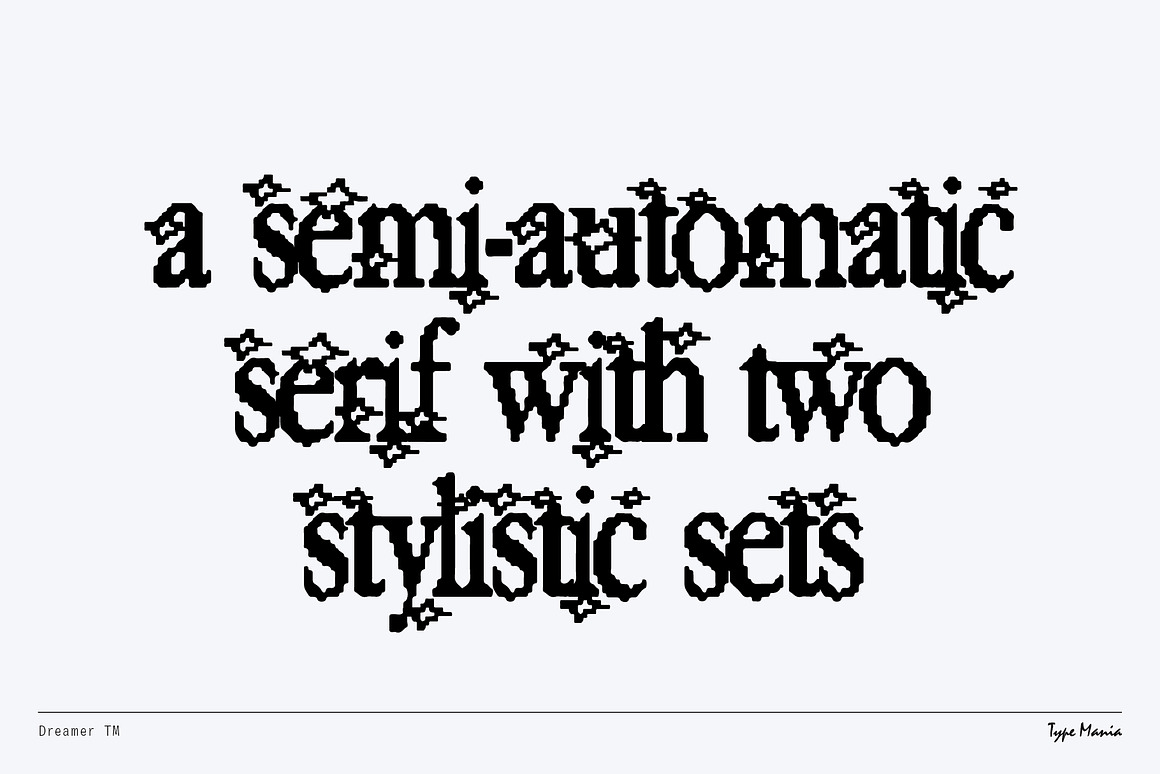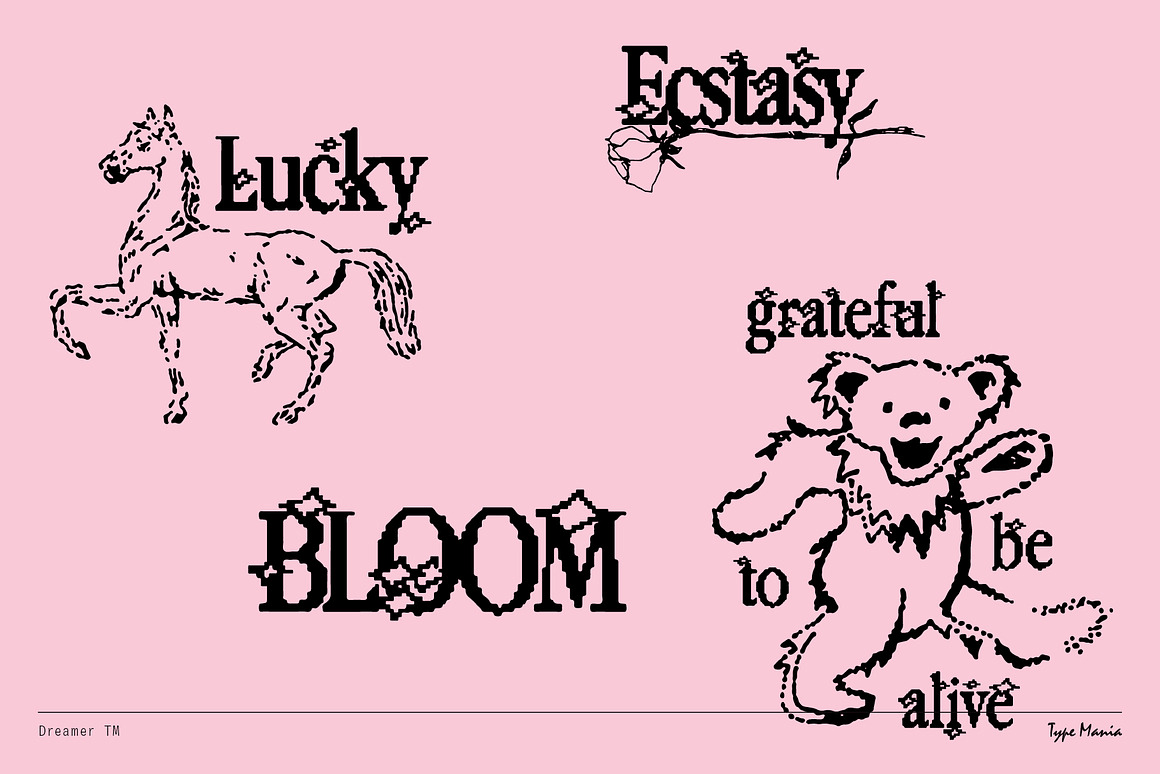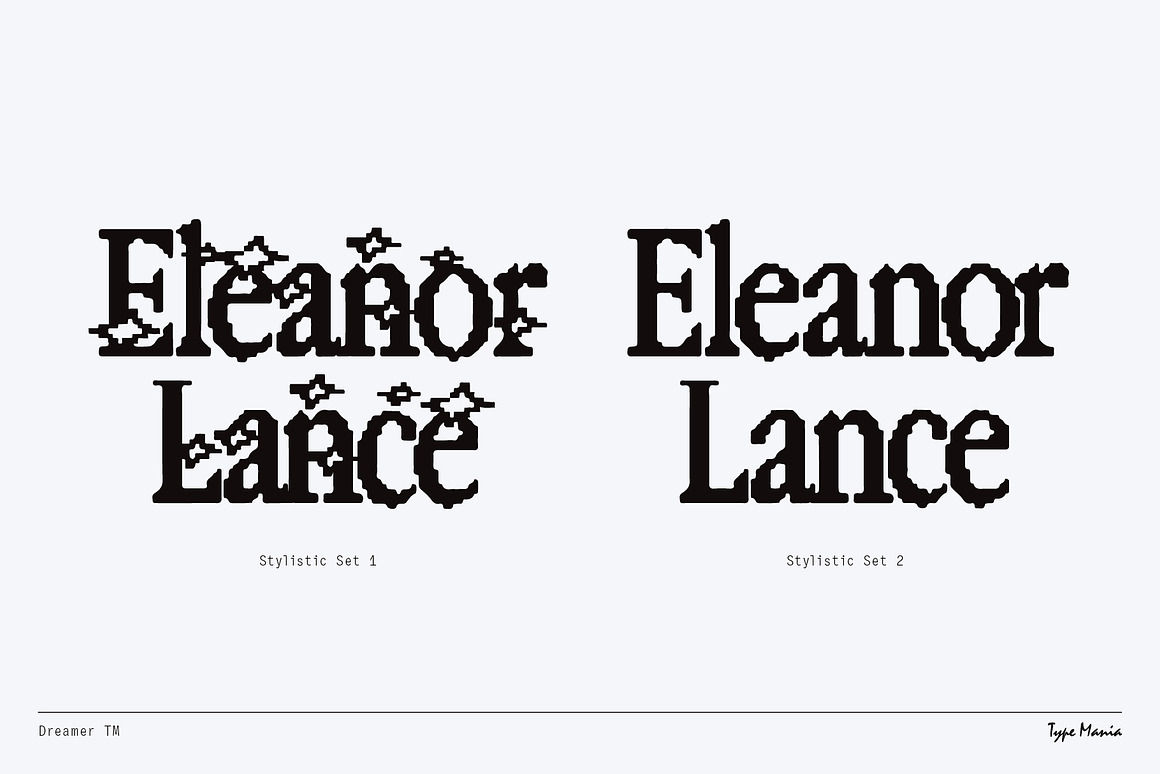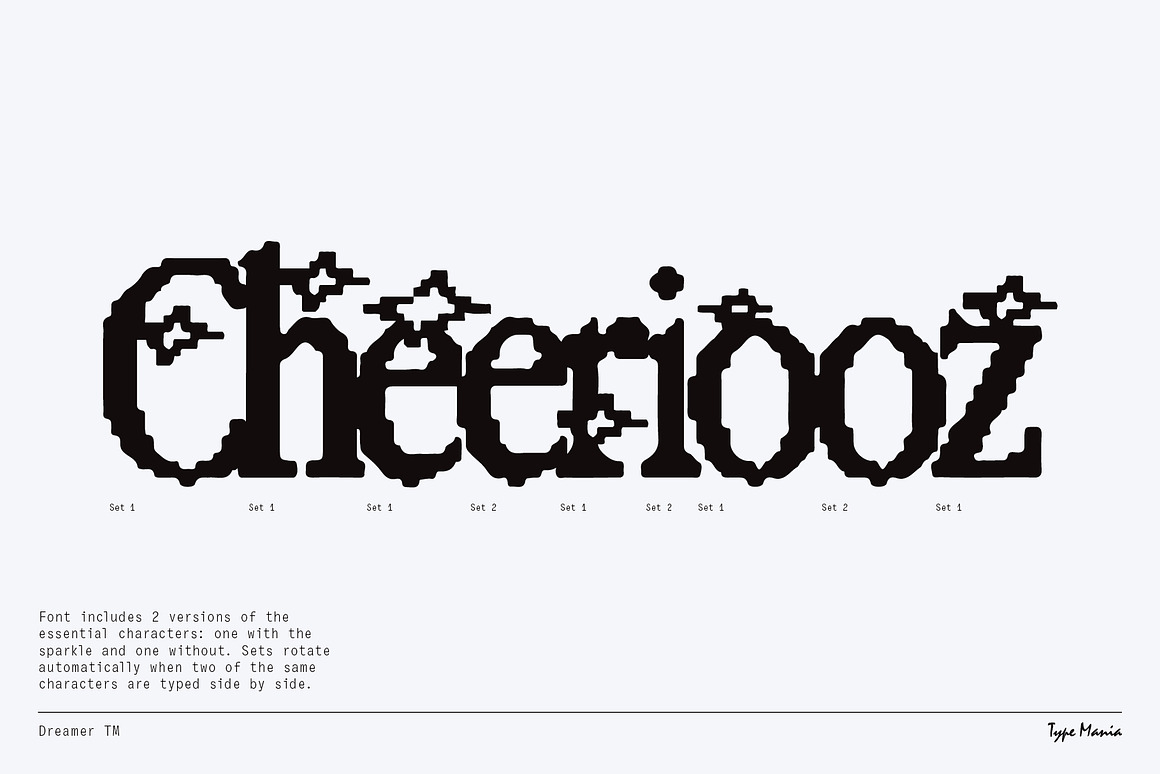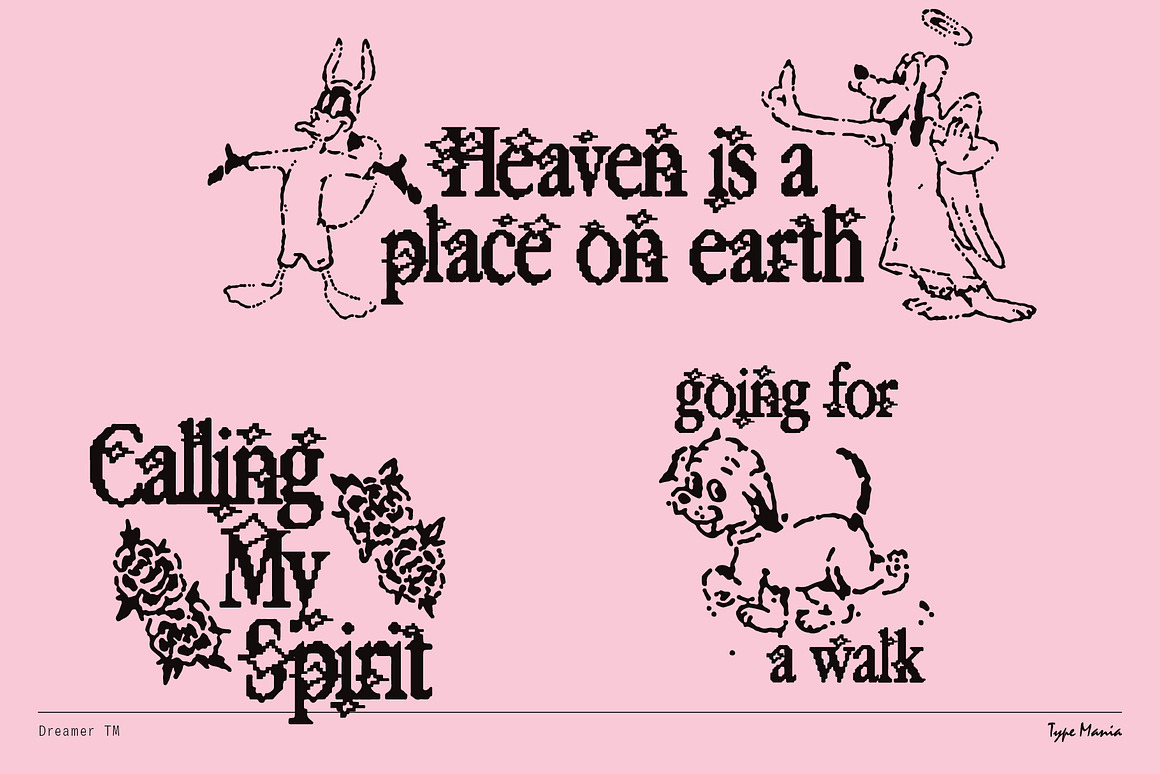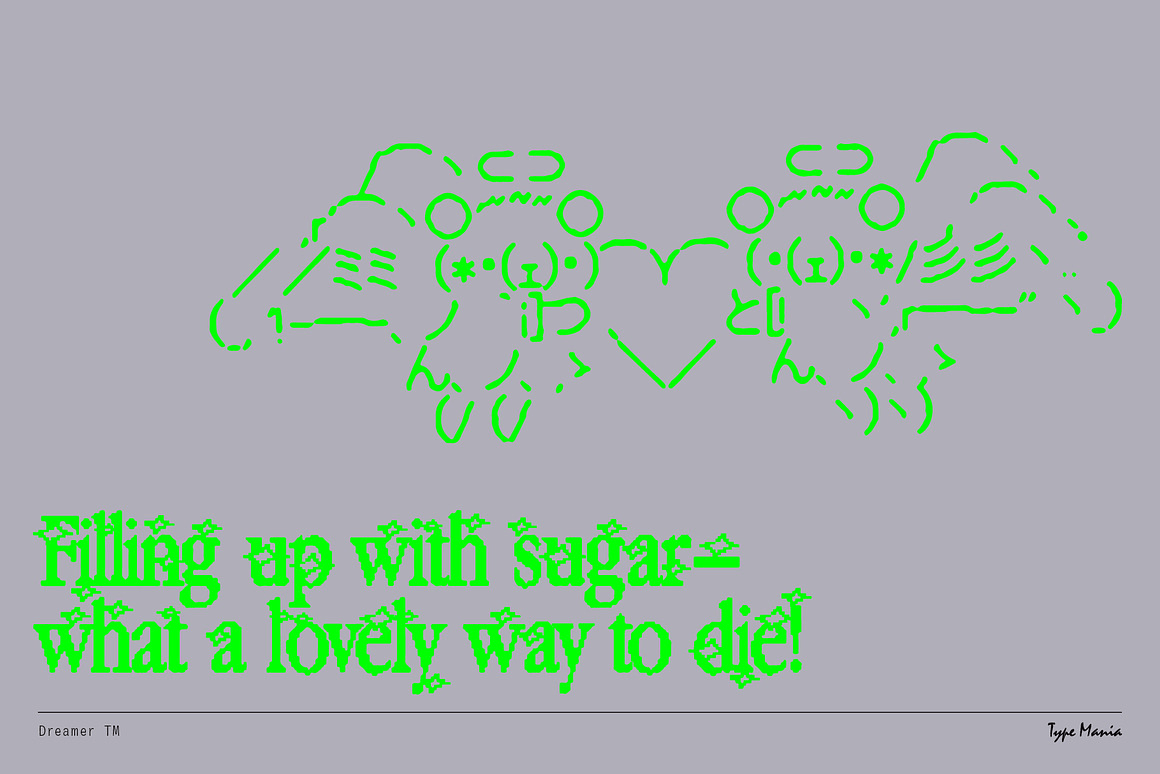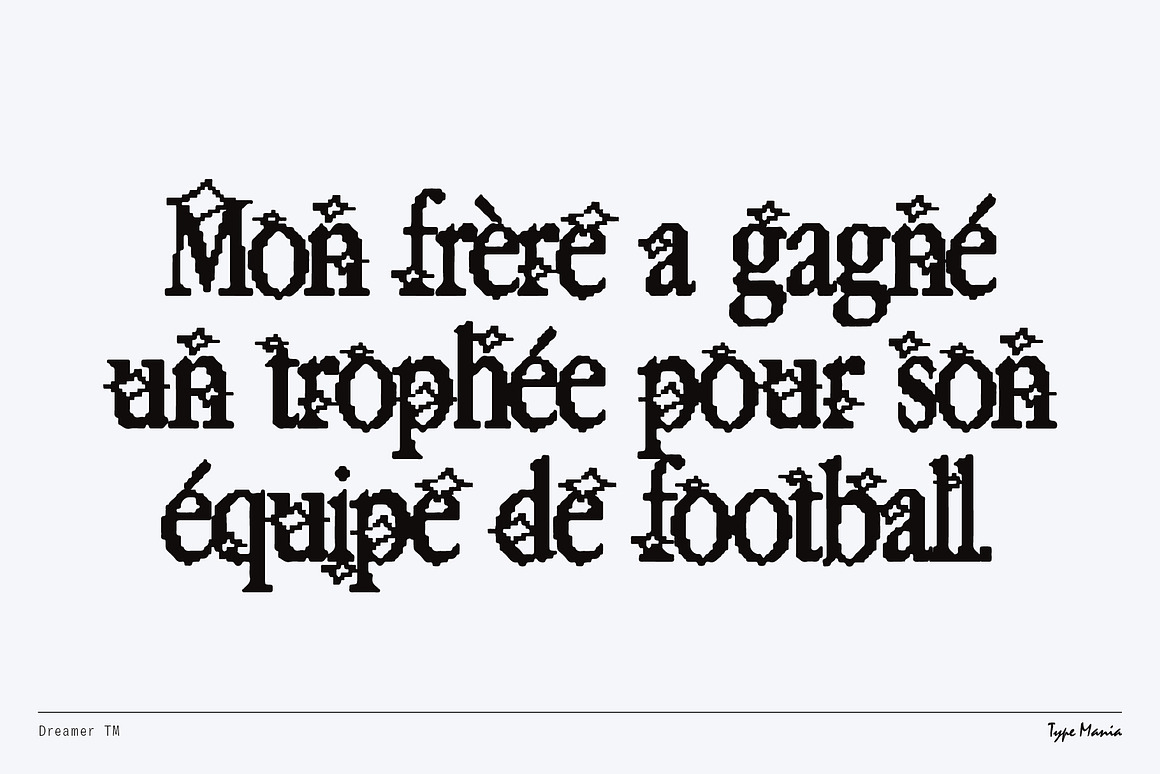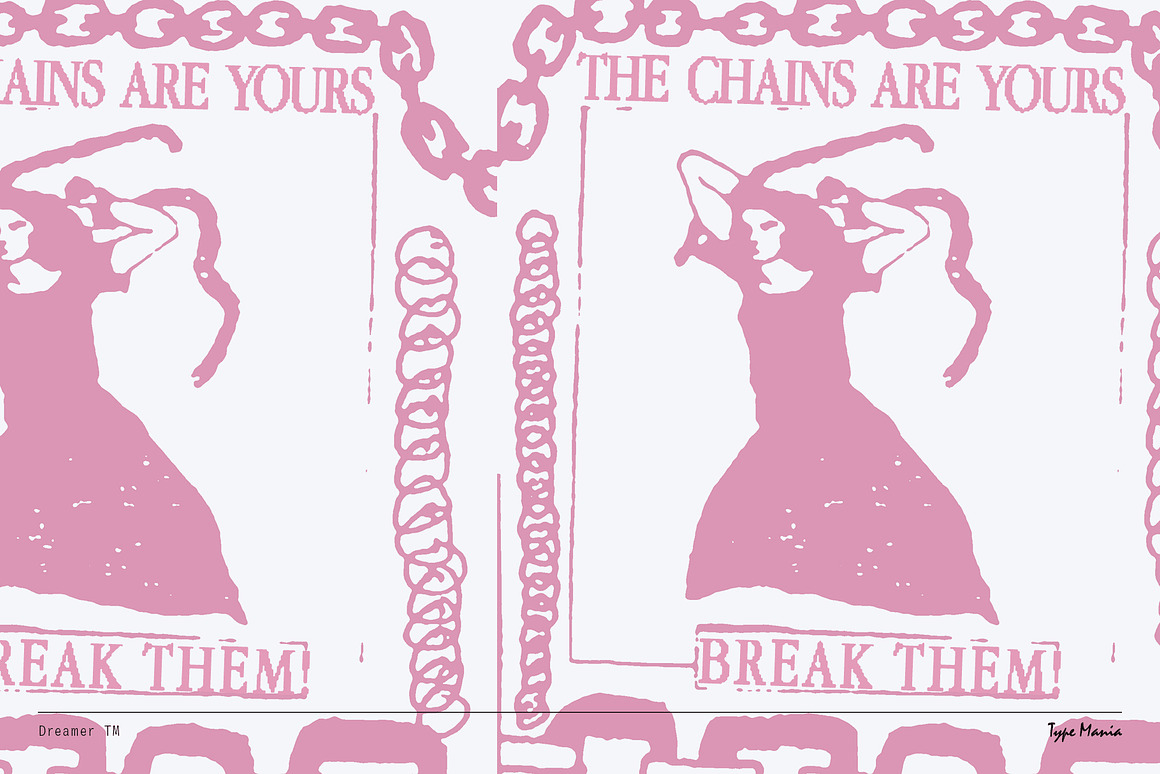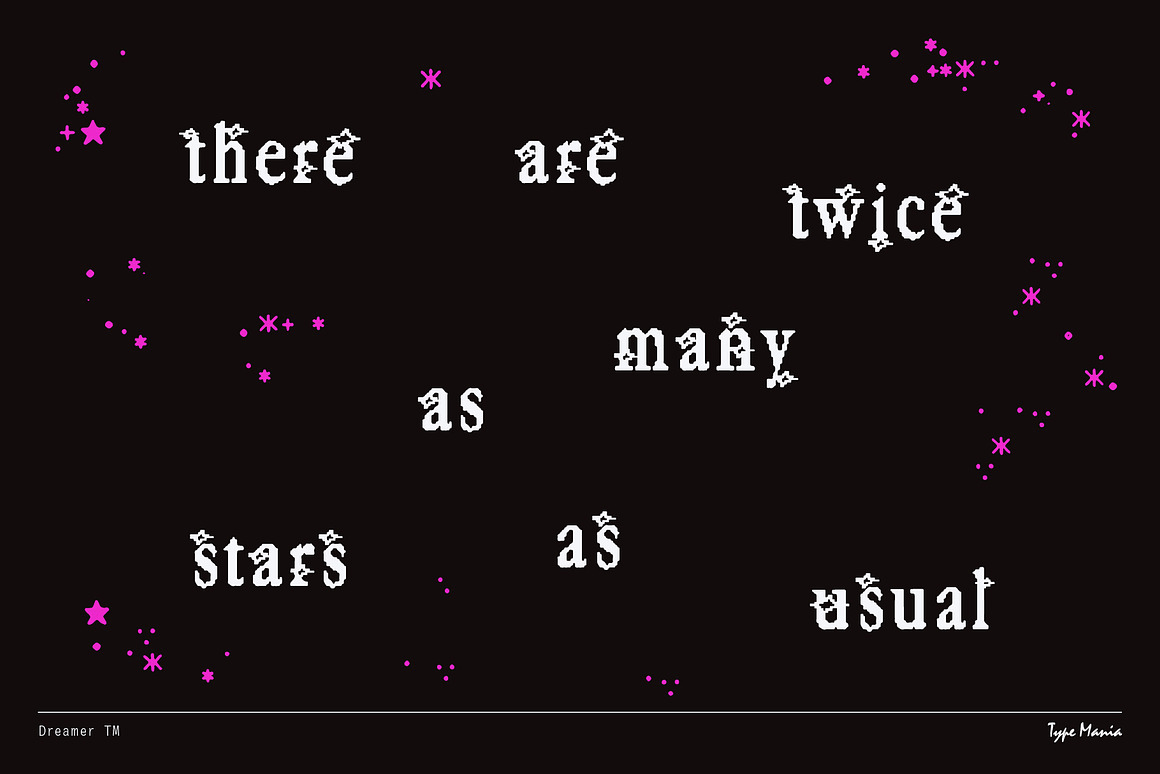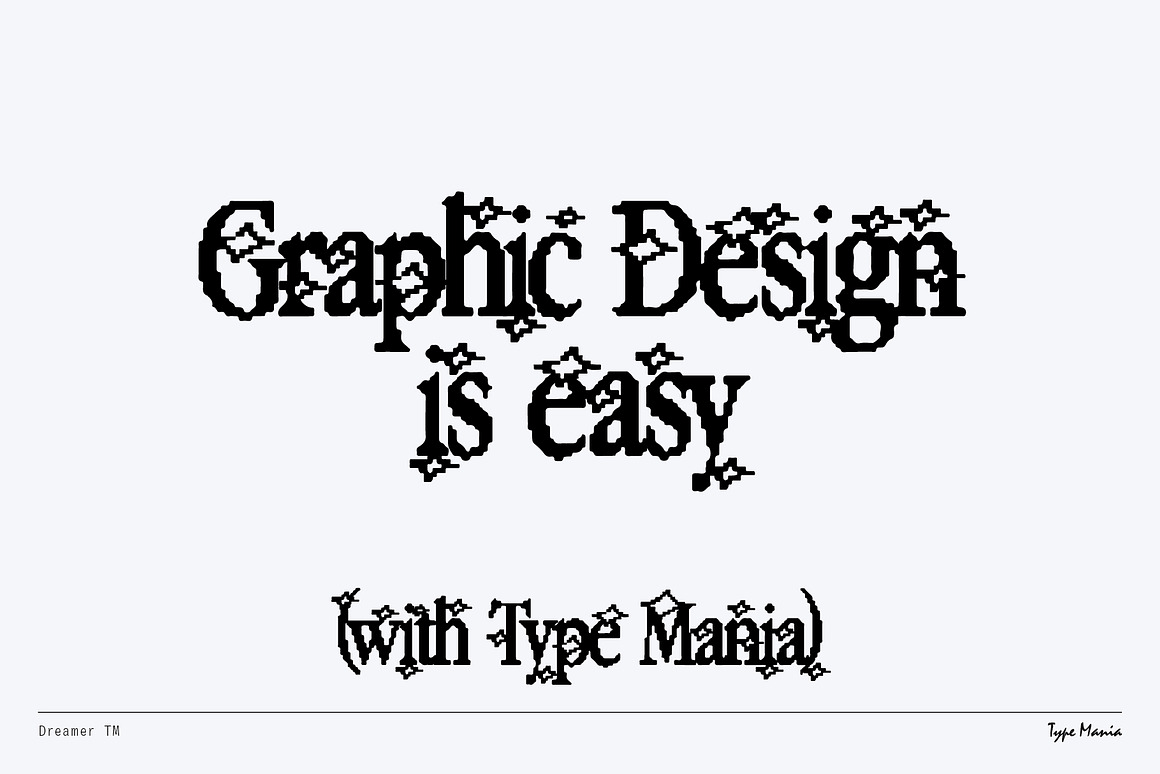
Bước vào thế giới kỳ diệu của Dreamer TM, phông chữ serif giàu cảm xúc của chúng tôi, khơi gợi phong cách thẩm mỹ Y2K. Dù bạn đang thiết kế poster, tạo logo hay thêm chút hoài niệm vào thương hiệu của mình, Dreamer TM sẽ mang đến một nét cá tính độc đáo cho dự án của bạn ⋆𐦍.ೃ࿔*:・
2 bộ kiểu dáng Phông chữ được lập trình để tự động chuyển đổi giữa các bộ kiểu dáng khi các ký tự giống nhau được gõ liền kề nhau.